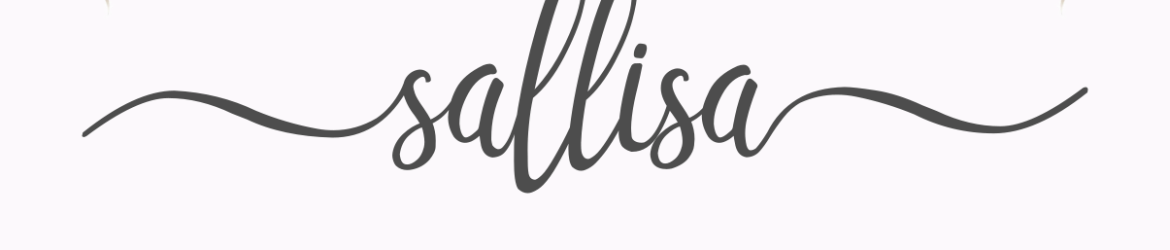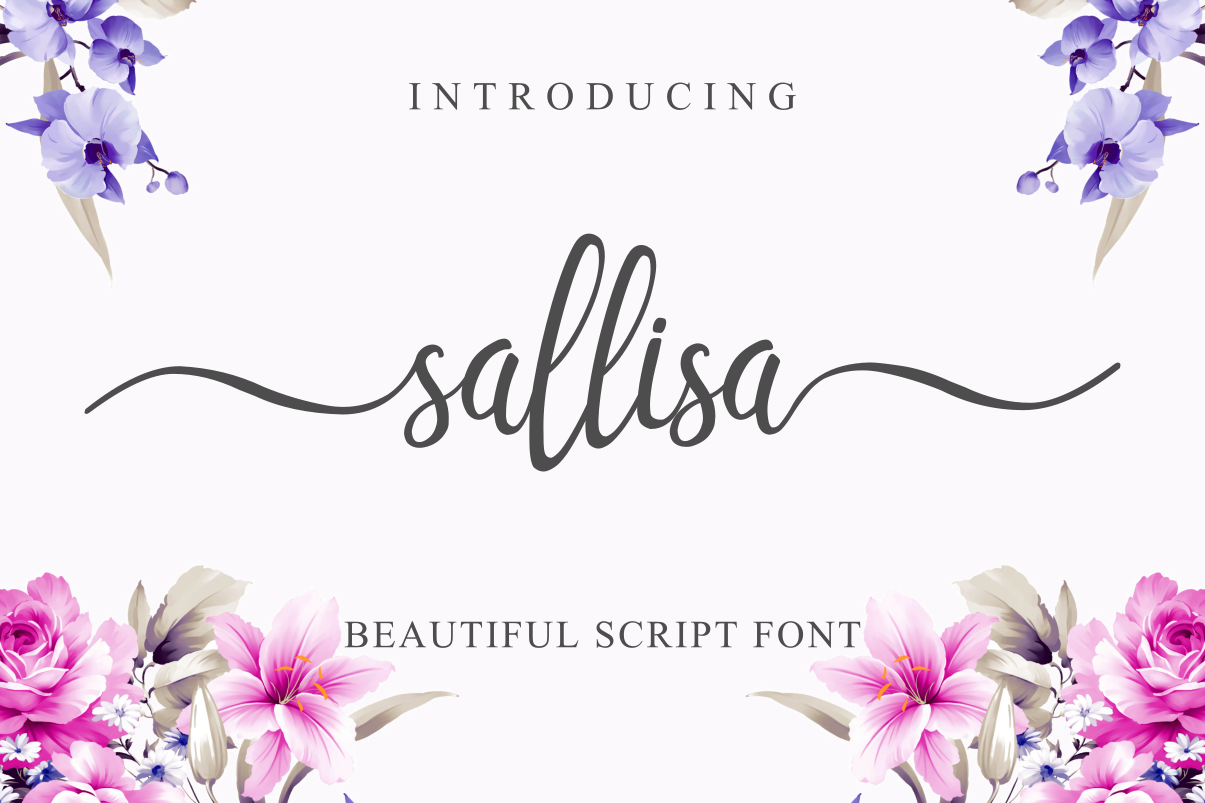
Sallisa Script Font – Fonte Grátis
Sallisa Script Font
A Sallisa é uma deliciosa fonte cursiva que se destaca por sua elegância moderna. Seu charme sofisticado a torna perfeita para adicionar um toque de luxo às suas criações. Seja você criando um design de revista, etiqueta de bolo ou qualquer outro projeto, essa fonte vai dar ao seu trabalho uma aparência única e impecável. A pandanwangi é o designer por trás desta obra-prima da gráfica, e ela certamente não deixará a sua impressão em nada que você escrever. Descubra a beleza deste design cuidadosamente projetado, disponível apenas na Sallisa Font para quem busca um ar de sofisticação no seu trabalho.
Designer: pandanwangi